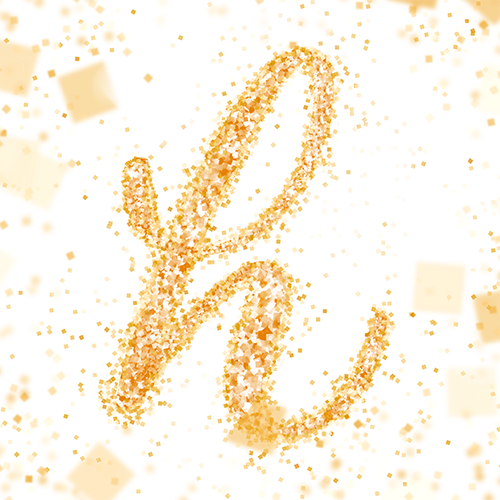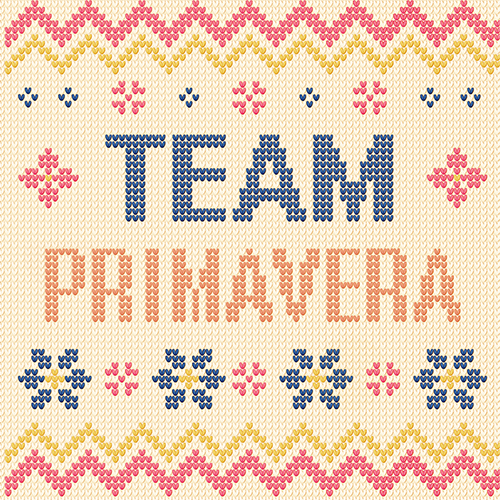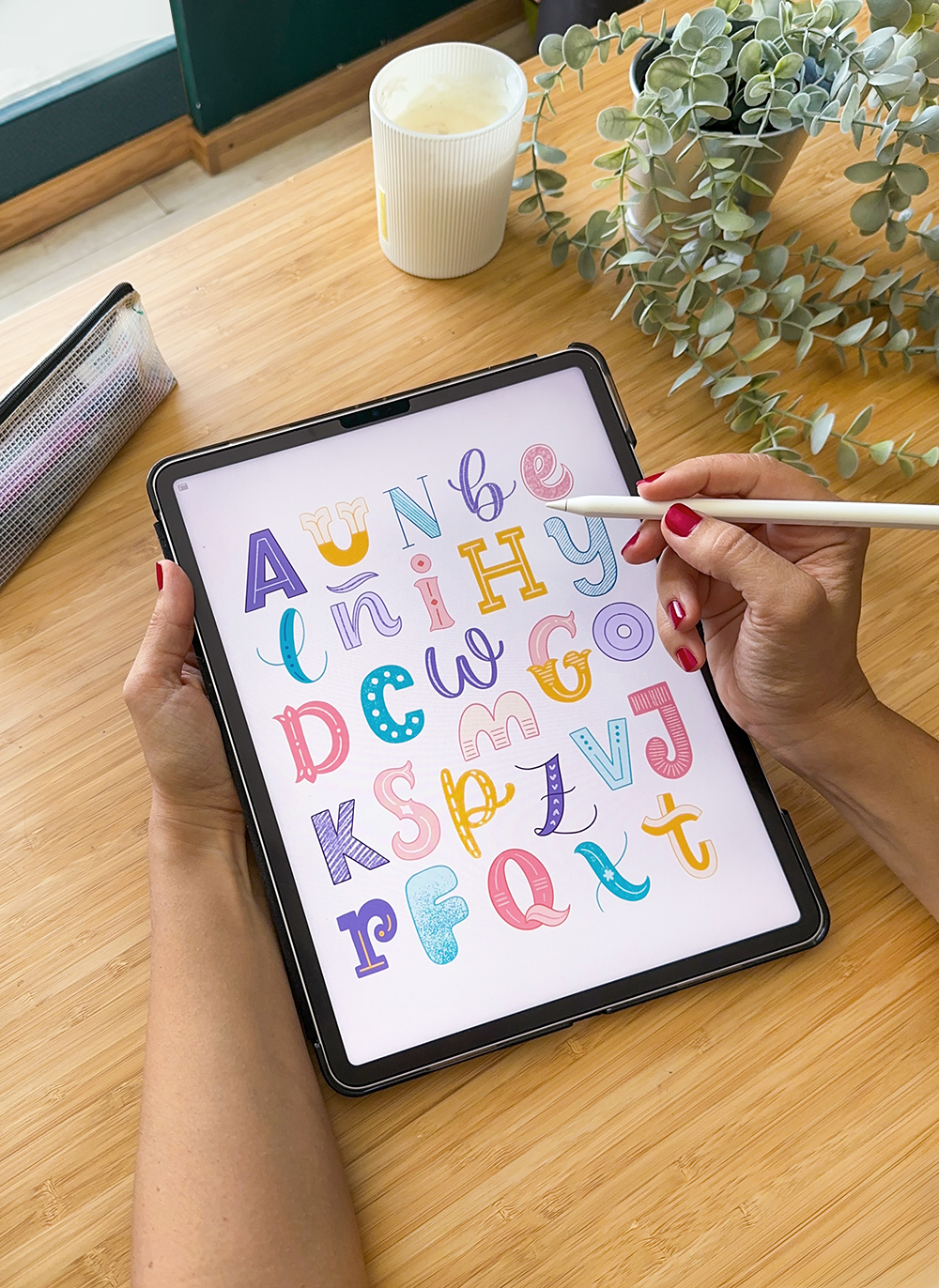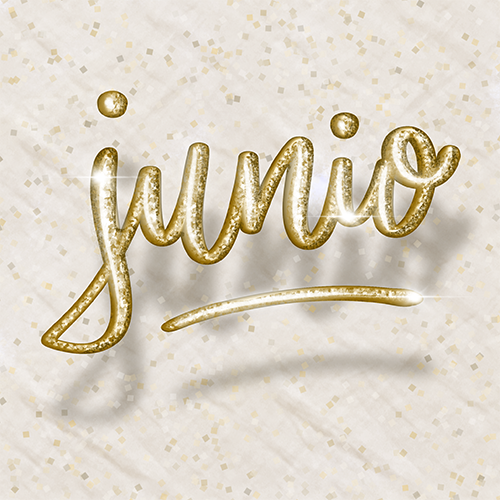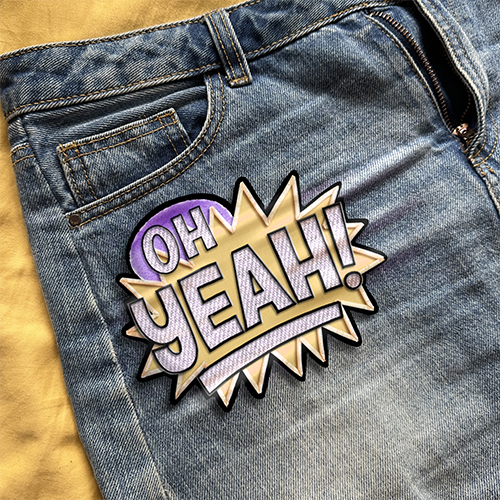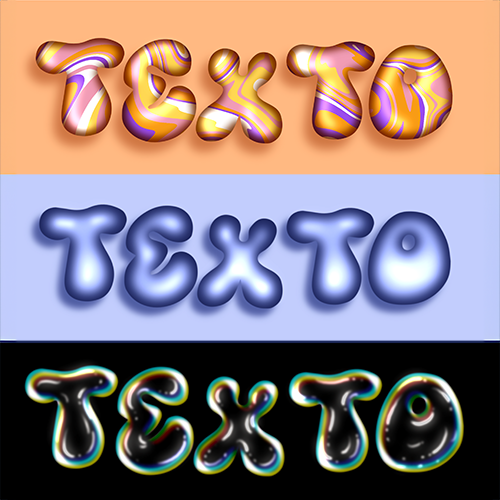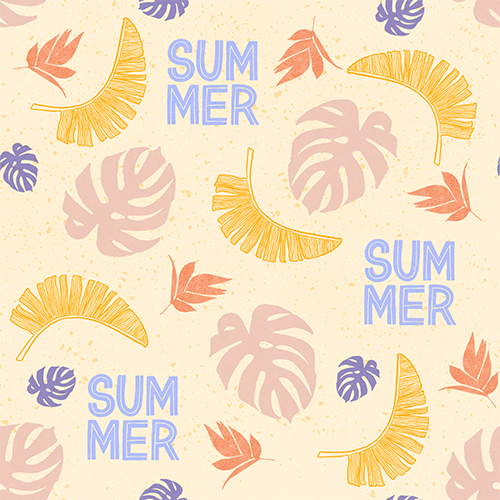
Aprende a crear y modificar pinceles en Procreate para crear efectos llamativos de un solo trazo. Combínalos con todas las herramientas de Procreate y diseña proyectos únicos.
Las clases incluyen pinceles específicos para cada proyecto que no se venden por separado, y que podrás utilizar en tus próximas creaciones.
Aquí tienes los proyectos que aprenderás a hacer
en estas clases:
Crea pinceles especiales
El estudio de pinceles de Procreate es una herramienta muy poderosa para crear pinceles nuevos con un montón de efectos distintos, aunque de primeras, intimida un poco. En estas clases aprenderás los mejores trucos para crear pinceles con resultados muy llamativos.
Diseña letterings impactantes
Con los pinceles que incluyen estas clases podrás dar volumen y textura a tus letras de una manera muy sencilla (casi casi automática ;). Los vídeos paso a paso te guiarán para que puedas conseguir el mismo resultado y puedas aplicarlo a tus propios proyectos.
Combina sellos en patrones de repetición
Los pinceles de sellos son muy útiles para crear fondos y patrones de repetición. En estas clases aprenderás a preparar una imagen para crear tus propios sellos, y a combinarlos para crear estampados con lettering e ilustración.
Aprende a tejer con Procreate
Las imágenes por píxeles, combinadas con pinceles de sello personalizados, te permiten recrear imágenes de muchos tipos. Un ejemplo son las texturas que conseguimos tejiendo con dos agujas... ¡pero completamente digital!
Utiliza texturas y mockups
Una vez creado tu diseño, aprenderás diferentes trucos para presentarlo de una manera original y divertida. Una de ellas es hacer un mockup, superponiendo tu dibujo a una fotografía, para dar más realismo a tus creaciones.
Convierte fuentes en letterings
con efecto
Para terminar, utilizaremos fuentes simples y las convertiremos en letterings con diferentes efectos, prácticamente sin esfuerzo, utilizando de la manera más avanzada las herramientas y ajustes de Procreate.